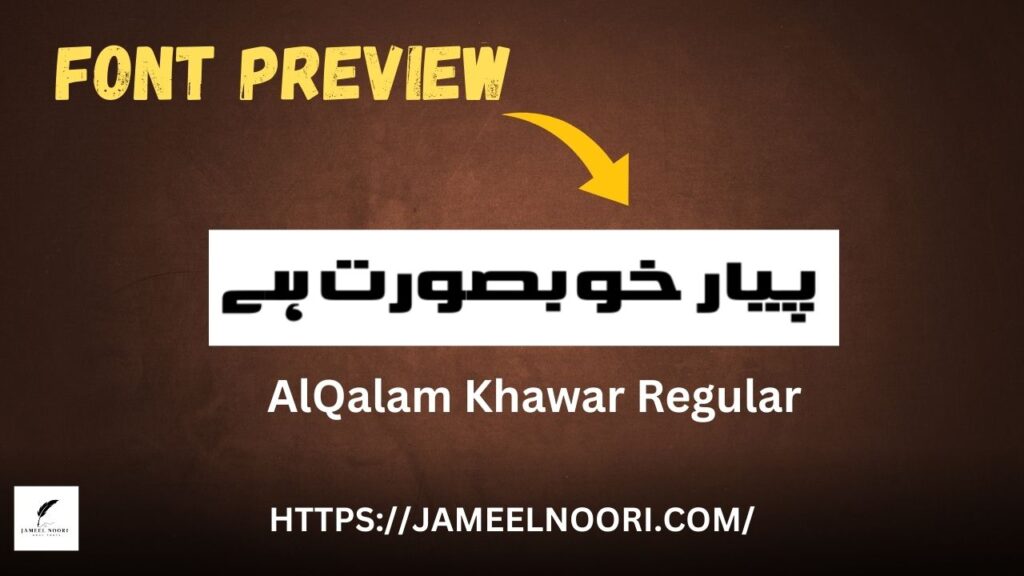
Urdu Font AlQalam Khawar Regular aik Regular TrueType Urdu font hai jo Urdu likhne walon, designers, aur calligraphers ke liye ek behtareen choice hai. Yeh font 6112 dafa download kiya ja chuka hai aur 13 users ne ise 3.17 out of 5 ka rating diya hai.
Features of Urdu Font AlQalam Khawar
- Stylish aur readable Urdu writing
Where You Can Use This Font
- Urdu Poetry Design
- Book Title Typography
- Social Media Post Design
- YouTube Thumbnails
- Website Headlines
5. Yeh font kis script mein likhta hai?
Yeh Urdu script ko True Nastaliq style mein support karta hai.
6. Kya is font mein ligatures available hain?
Is font mein basic Urdu ligatures hain jo isay readable banate hain.